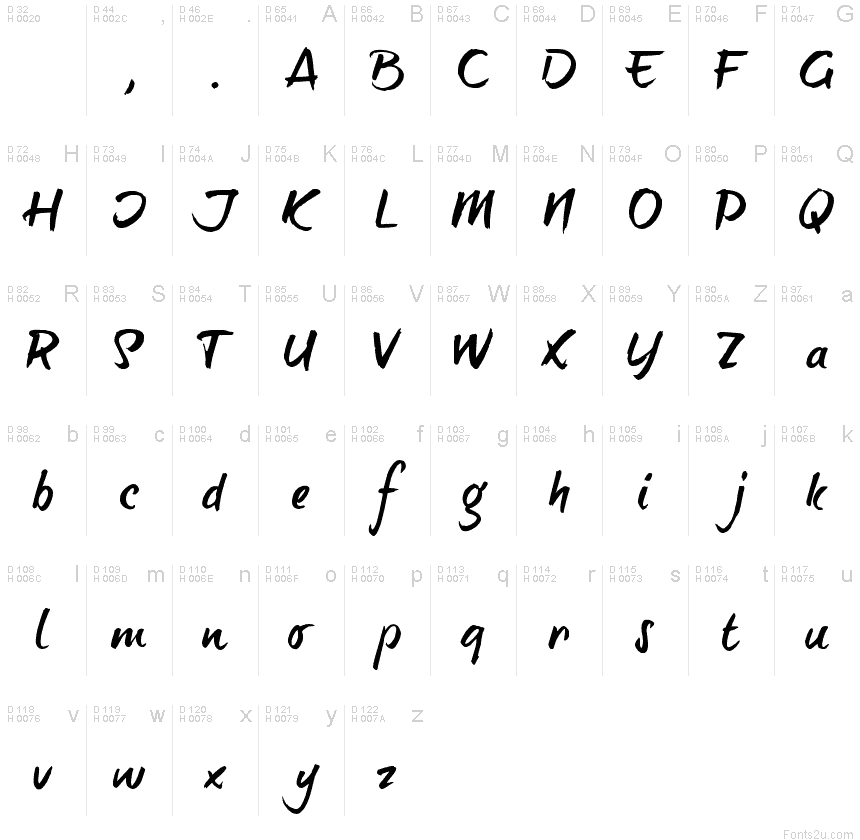
brush-tipTerrence 字体
brush-tipTerrence
JOEBOB Graphics
JJW van der Ham
Brush Tip Terrence 由 Joebob Graphics 出品,是一款免费的笔刷字体,笔触灵动,充满手绘质感。字母仿佛是用吸满墨水的马克笔或画笔写就,粗线条、尖锐的笔锋与略显粗糙的边缘相互交织,使字形线条生动活泼,而非刻板平滑。
它非常适合需要展现非正式手写风格的设计作品,例如海报标题、咖啡馆品牌形象、专辑封面、包装设计以及社交媒体卡片。作为一款免费字体,它在短小精悍的文案中表现最佳,其宽阔的笔刷纹理和随性的节奏,能为简单的短语赋予一种休闲而又亲切的手作感。